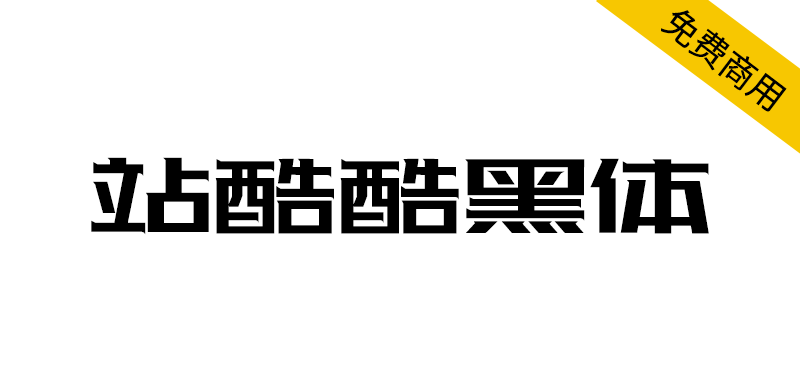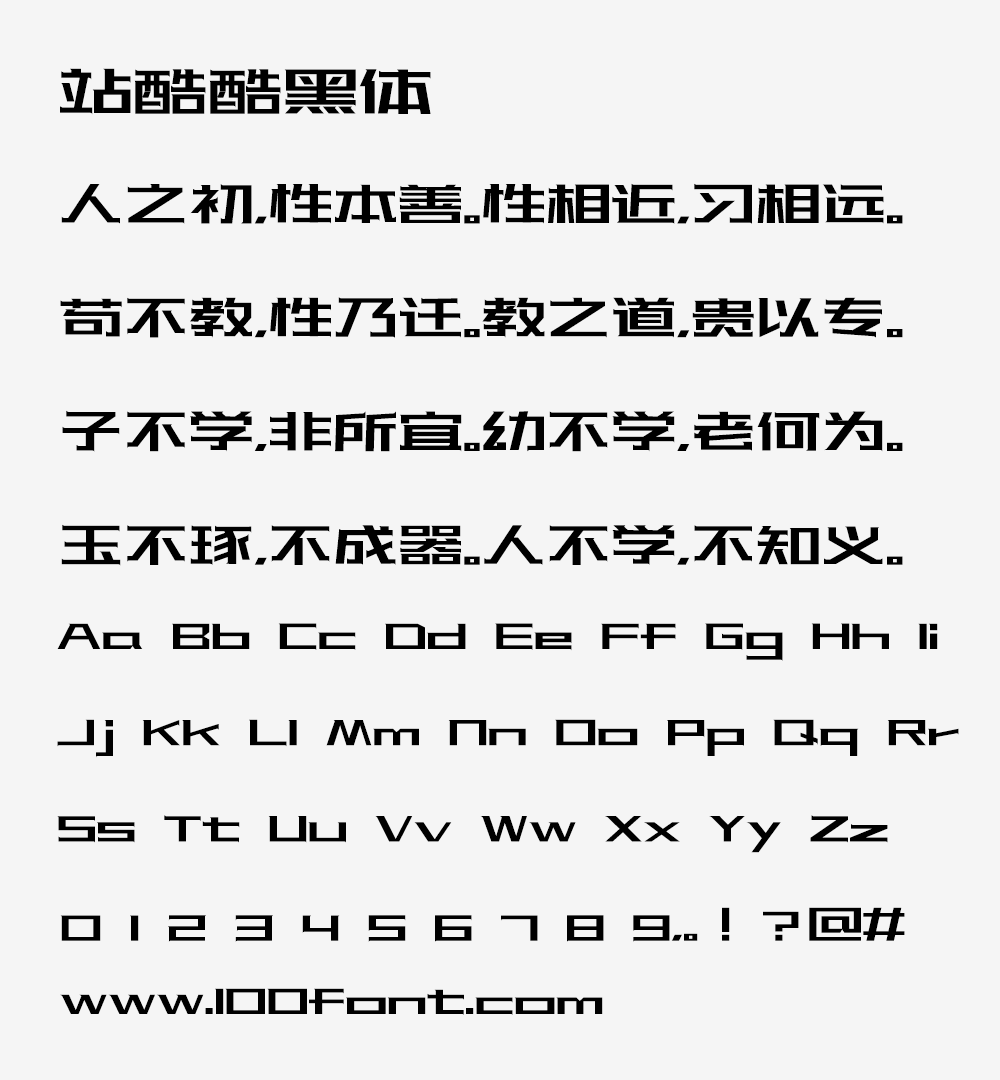
[站酷酷黑体]发布于2016年7月,恰逢在站酷十周年之际,横空出世。由胡晓波发起,字游工作室成员进行基础字形设计,胡晓波设计班十名学员共同设计完成。包含3500个常用字、52个英文字母、10个阿拉伯数字。
[站酷酷黑体]由胡晓波发起,字游工作室成员进行基础字形设计,胡晓波设计班十名学员共同设计完成。
[站酷酷黑体] 字形笔画粗犷有力、用宽扁型的字面构建出厚重的字体形态,笔画细节上的修饰既增强了字体的设计感,又让字体多了一些小小的精致感。这套字体的中宫非常饱满,使得文字之间的排版组合非常醒目好看;
关于站酷字体:站酷公益字体,源自2014年的一次公益造字活动。由站酷ZCOOL的活跃字体设计师胡晓波及刘兵克发起这个项目,并设计最初的字形规范及基本部首,其余字形以众包的形式由分散在全国的79名设计师分别完成,最终一套好用并且免费的中文字体“站酷高端黑”诞生并在2014年圣诞发布。自从站酷高端黑之后,有更多的设计师团队和个人将字体赠送给站酷公益字体项目,交由站酷传播,给更多设计师使用。
一套标准的中文字库包含6000多个汉字,制作中文字体是一件非常困难的事情,现有的中文字体也远远满足不了设计师们的需求。因而站酷公益字体受到很多设计师的欢迎。
字形笔画粗犷有力、用宽扁型的字面构建出厚重的字体形态,笔画细节上的修饰既增强了字体的设计感,又让字体多了一些小小的精致感。这套字体的中宫非常饱满,使得文字之间的排版组合非常醒目好看。